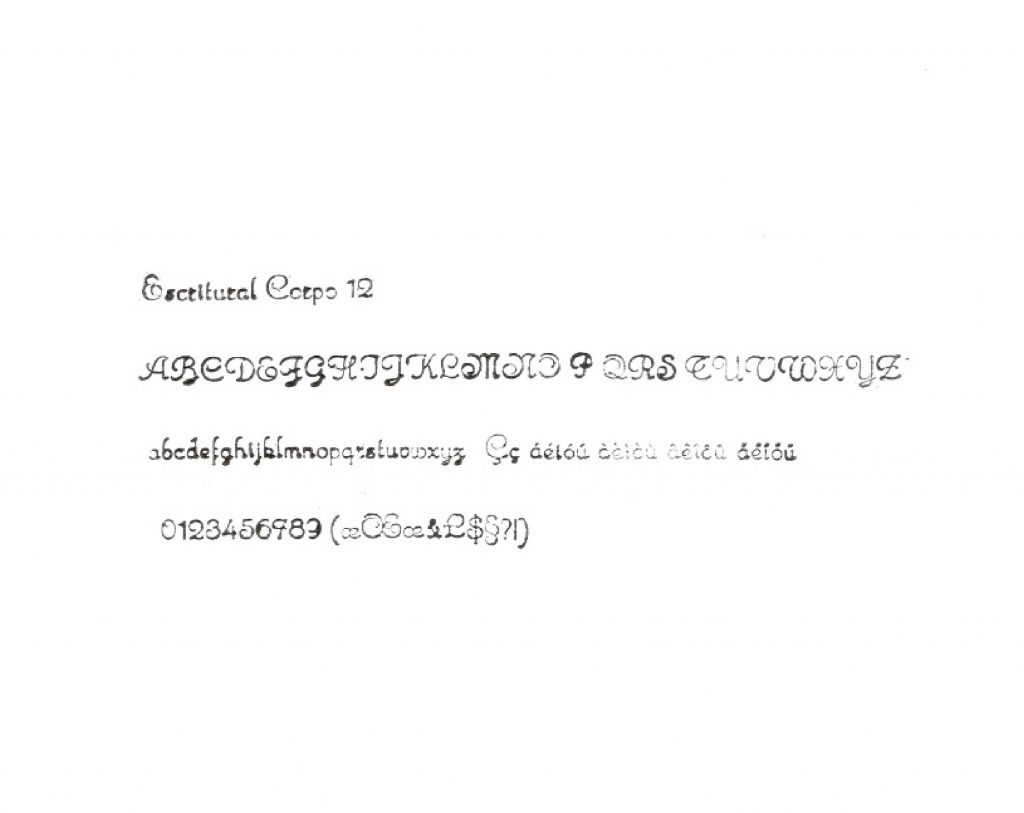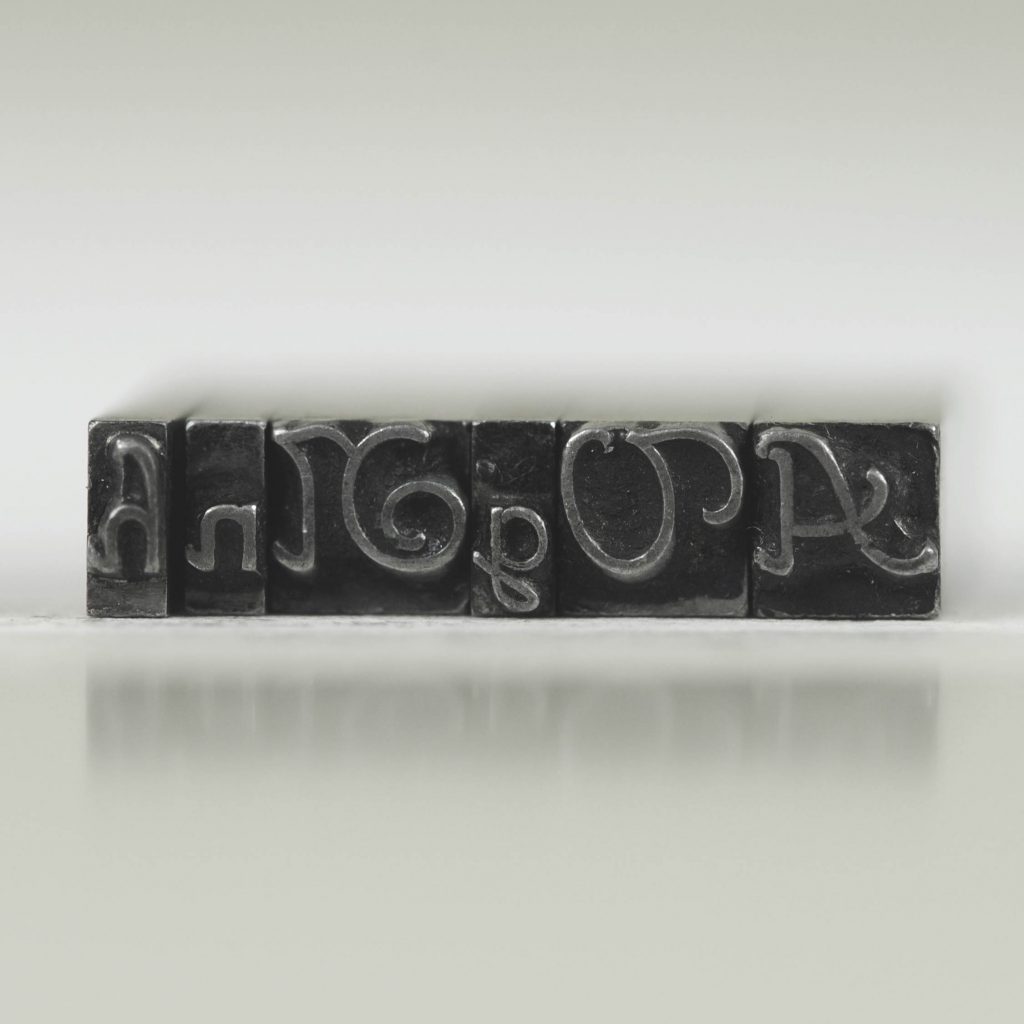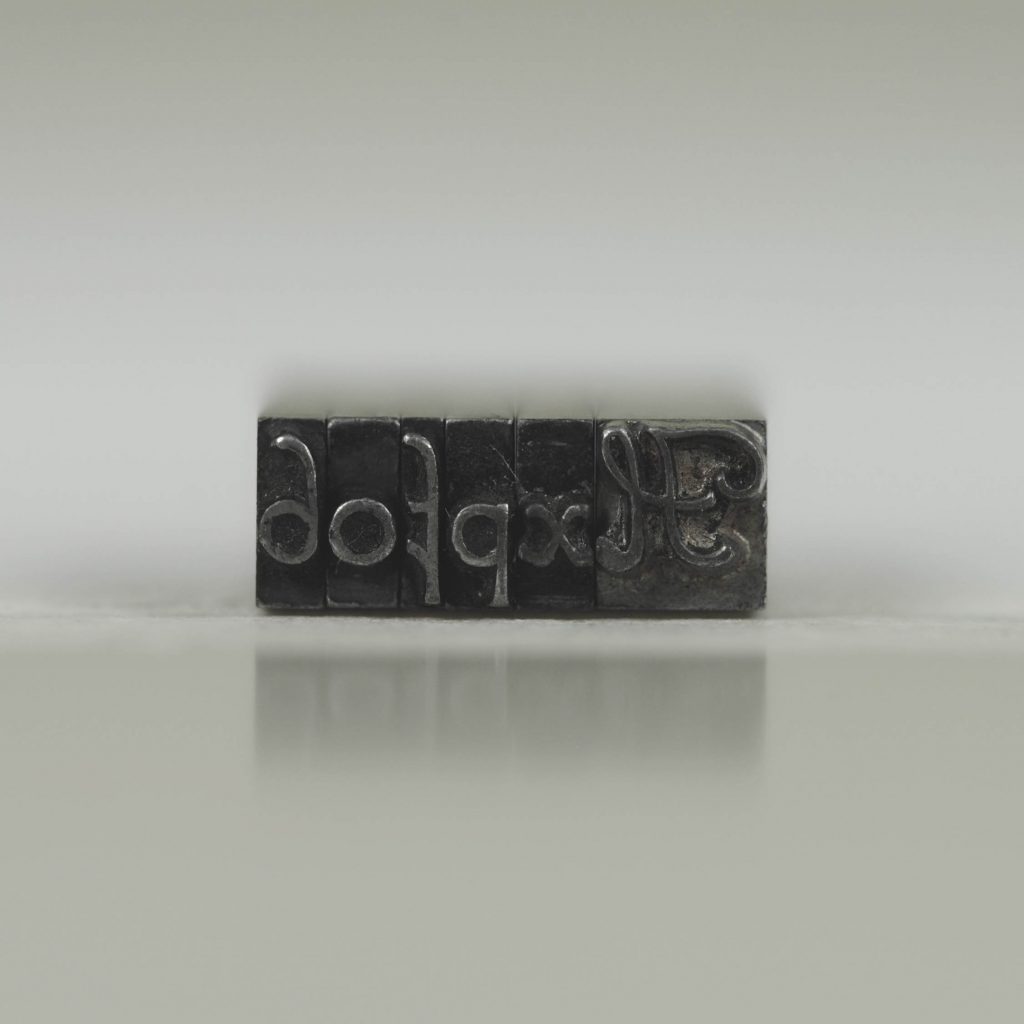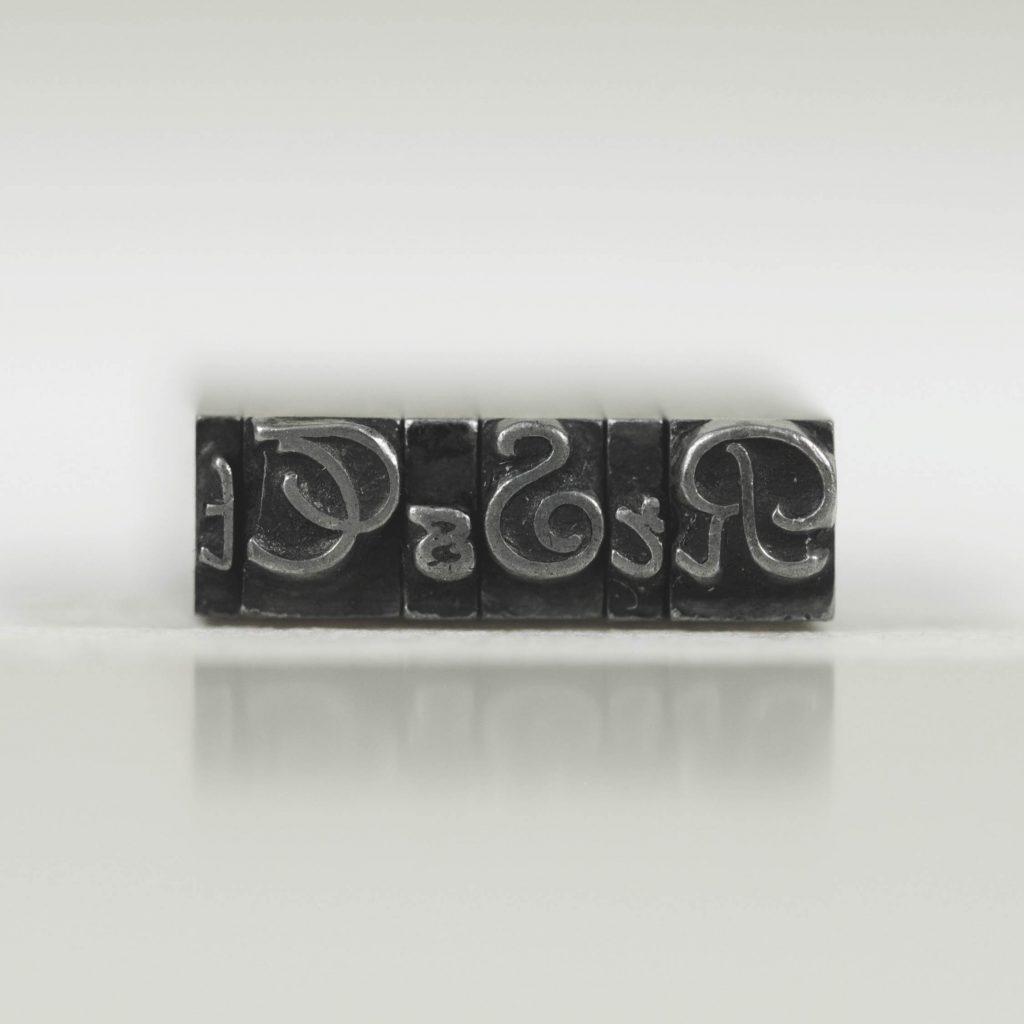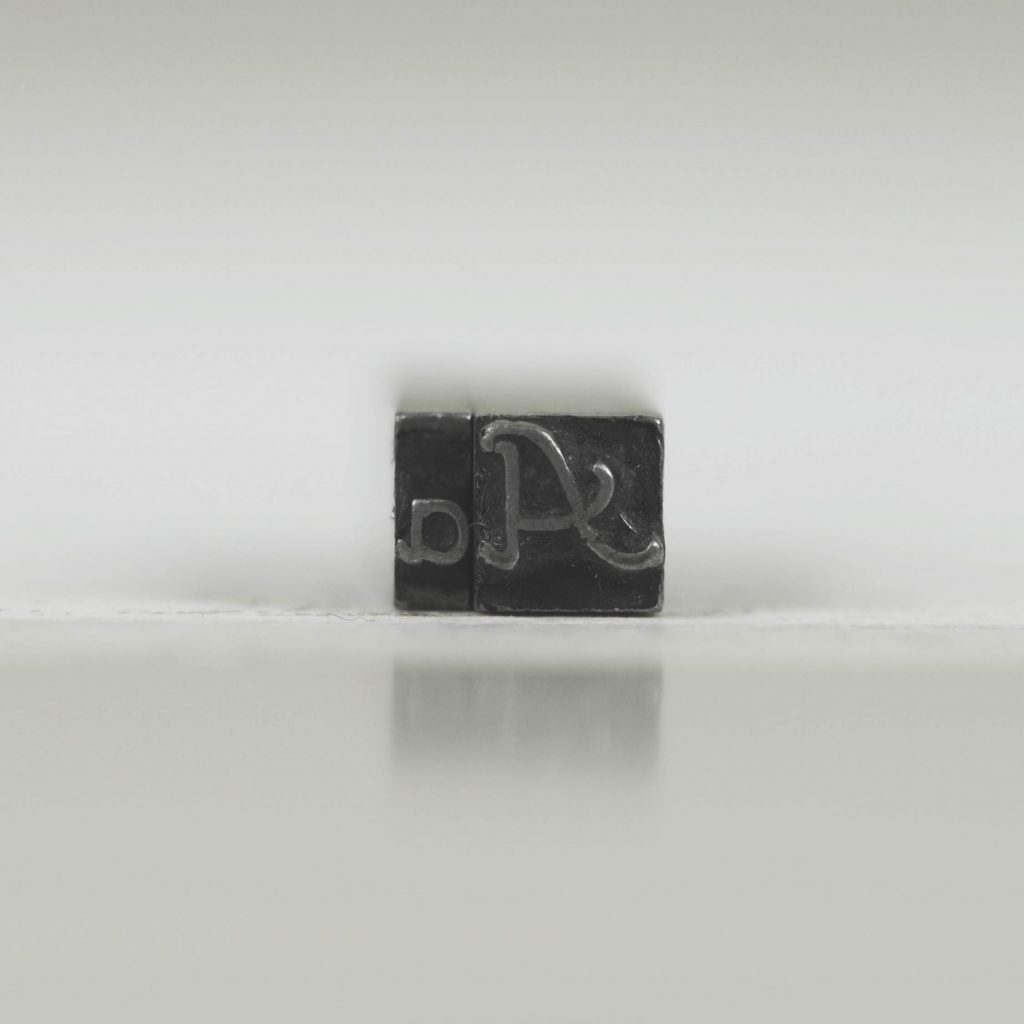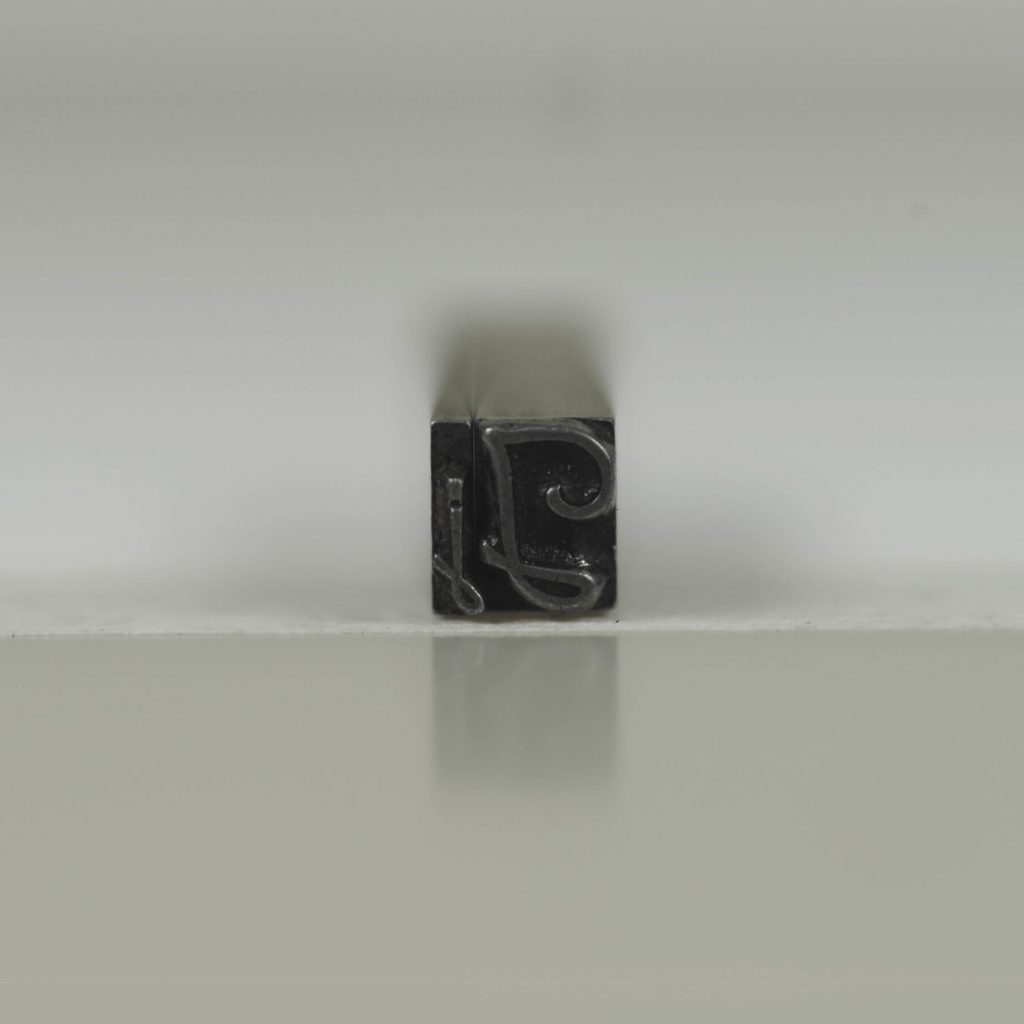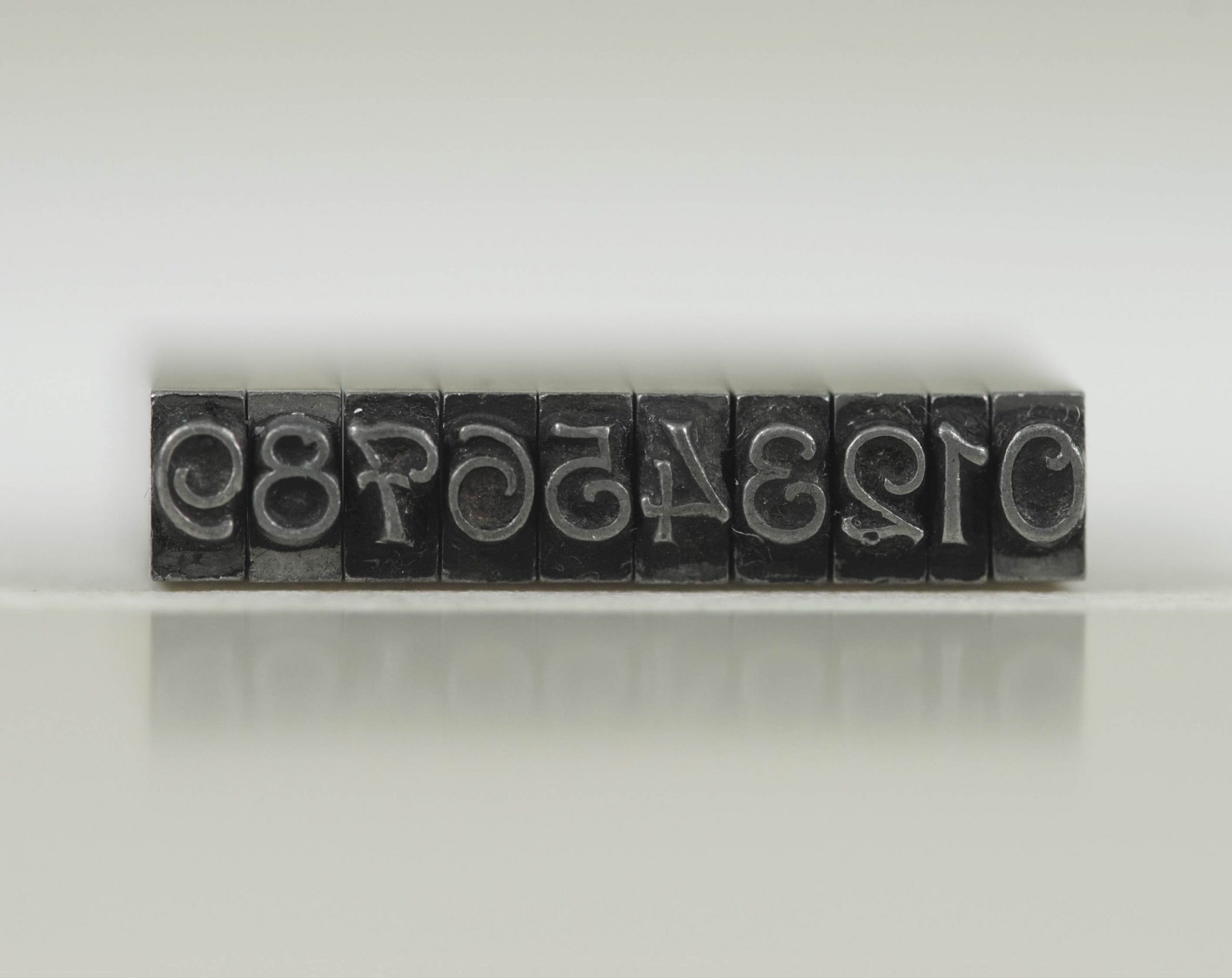
Athenas 12pt
Estilo
Escritural
Corpo (pt)
12
Caracteres Chave
A, M, T, vogais com acentos agudo duplos
Fundidora
Funtimod
Catálogo
Funtimod S.A. [entre 1958 e 1963] [capa laranja]
Tipo de Inscrição
Rasgo concavo
Localização da Inscrição
Base do tipo
Estado de Conservação
Marcas de uso recorrente; alguns tipos apresentam desgaste na face que pode comprometer a qualidade da impressão.
Quantidade Total de Tipos
1479
Disponibilidade
Maiúsculas | Minúsculas | Maiúsculas acentuadas | Minúsculas acentuadas | Numerais | Sinais | Pontuações | Poucas ligaturas
Semelhanças e Diferenças
Por se tratar de uma réplica, a variante da Funtimod apresenta algumas características diferentes. Dentre elas, a forma da letra “R” minúscula é particularmente significativa, com suspeitas de que essa variação seja exclusivamente brasileira. Essa alteração pode refletir preferências estéticas da escrita da época (por se tratar de uma fonte que se assemelha com a escrita cursiva) (Aragão, 2016 p. 208).
História do Estilo
Após análises comparativas sabe-se que se trata da fonte Athenas, comercializada pela fundidora Funtimod (Aragão, 2016). A identificação se deu em um catálogo da Funtimod [1958 e 1963] provavelmente impresso na década de 1960 (Aragão, 2016). Sabe-se que o desenho original dessa fonte foi comercializado como Isolde pela fundidora alemã Wagner & Schmidt desde 1912 (Wetzig, 1926).